Как заставить шрифты в Windows выглядеть как в Mac OS
Можно долго спорить про отдельные преимущества разных операционных систем, но с некоторыми фактами трудно не согласиться даже самым ожесточённым противникам. Например, ни у кого не вызывает сомнения то, что дизайн операционных систем от Apple гораздо детальнее проработан и является своего рода эталоном для конкурентов. Это же касается и рендеринга шрифтов.
Хотя в Microsoft существует и применяется своя система сглаживания под названием ClearType, всё же многие предпочли бы тот метод, который используется в Mac OS. И помогут нам в этом небольшие утилиты Gdipp и MacType.
Gdipp — это открытый проект независимых разработчиков, который направлен на создание альтернативной технологии рендеринга шрифтов в среде Windows. При этом обеспечивается более гладкое и приятное для глаз начертание шрифтов, подобное тому, что мы видим в Mac OS и некоторых дистрибутивах Linux.
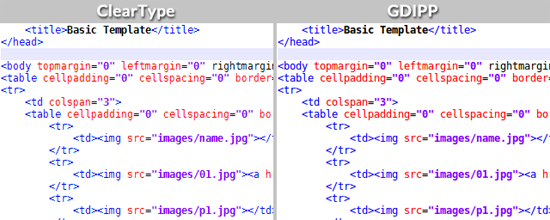
MacType
Эта программа, как и рассмотренная выше Gdipp, имеет в своей основе закрытый ранее проект GDI++. Основная функциональность точно такая же, но есть некоторые дополнительные опции, с помощью которых вы сможете более детально настроить отображение букв.
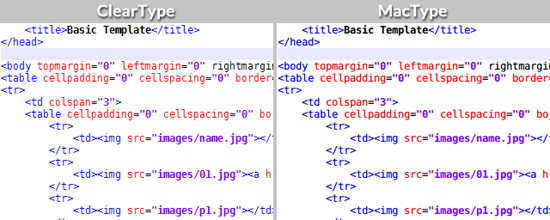
Судя по отзывам пользователей, работа программ MacType и Gdipp вызывает довольно неоднозначные оценки. Одним вид новых шрифтов чрезвычайно нравится, другие не видят в них ничего особенного и возвращаются к стандартному ClearType. А каково ваше впечатление?